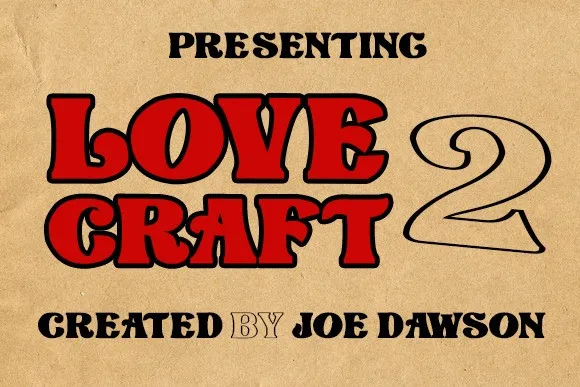
A “Love Craft 2 Font” é uma elegante e tradicional fonte serif que se destaca pela sua simplicidade única e descontraída. Seu design bold e clean, criado por Joe Dawson, pode ser facilmente adaptado para uma ampla variedade de aplicativos gráficos. Kharinniswa sugere o uso desta fonte especialmente em títulos, headlines, capas, selos, logotipos, citações, embalagens de produtos e até mesmo cartões de agradecimento, proporcionando um toque único que torna cada projeto uma verdadeira obra-prima. Ideal para designers procurando uma alternativa moderna às fontes mais convencionais, esta é uma escolha inspiradora para aqueles que valorizam estilos distintos e elegantes.